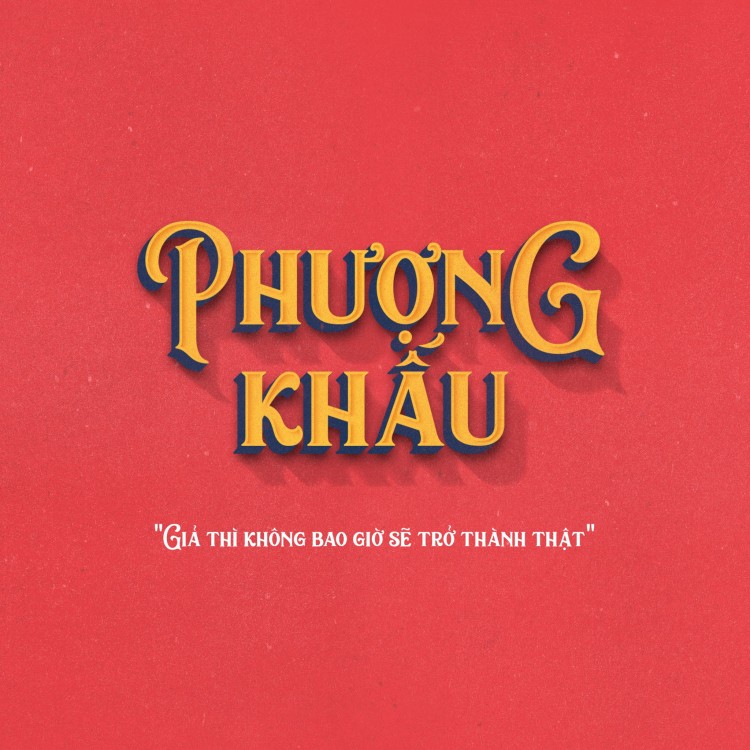
Font việt hóa LNTH Sacred Bridge
Font việt hóa LNTH Sacred Bridge – Nghệ thuật cổ điển cho thiết kế hiện đại
Trong thế giới đồ họa hiện nay, việc lựa chọn một bộ Font Miễn Phí chất lượng đóng vai trò vô cùng quan trọng để tạo nên linh hồn cho tác phẩm. Font việt hóa LNTH Sacred Bridge là một đại diện tiêu biểu cho phong cách hiển thị cổ điển, mang đậm hơi thở của những năm đầu thế kỷ trước. Với sự kết hợp tinh tế giữa nét chữ cứng cáp và các đường uốn lượn đặc trưng, bộ font này không chỉ giúp bài thiết kế trở nên chuyên nghiệp mà còn gợi lên cảm xúc hoài cổ đầy ấn tượng cho người xem.
Đặc điểm nổi bật của Font việt hóa LNTH Sacred Bridge
Bộ Font việt hóa LNTH Sacred Bridge được các nhà thiết kế ưa chuộng nhờ tính linh hoạt cao trong nhiều bối cảnh khác nhau. Từ các biểu tượng logo sang trọng đến bìa sách giáo dục hay các ấn phẩm truyền thông nhà trường, font chữ này đều thể hiện được sự chỉn chu và độc đáo.
Phong cách Typography đậm chất Vintage
Cấu trúc của font tập trung vào các đường nét lấy cảm hứng từ phong cách Victoria, tạo nên một vẻ ngoài vững chãi nhưng không kém phần mềm mại. Việc sử dụng Font việt hóa LNTH Sacred Bridge giúp các bạn học sinh, sinh viên dễ dàng tạo ra những slide thuyết trình hoặc báo cáo thực tập có tính thẩm mỹ cao, thu hút sự chú ý của thầy cô ngay từ cái nhìn đầu tiên.
Khả năng hiển thị và tính tương thích
Phiên bản việt hóa này đã được tối ưu hoàn toàn về các dấu câu tiếng Việt, giúp người dùng không còn lo lắng về lỗi font khi gõ nội dung. Điều này cực kỳ hữu ích cho các dự án thiết kế thuần Việt cần sự tỉ mỉ trong từng ký tự.
Ứng dụng Font việt hóa LNTH Sacred Bridge trong thực tế